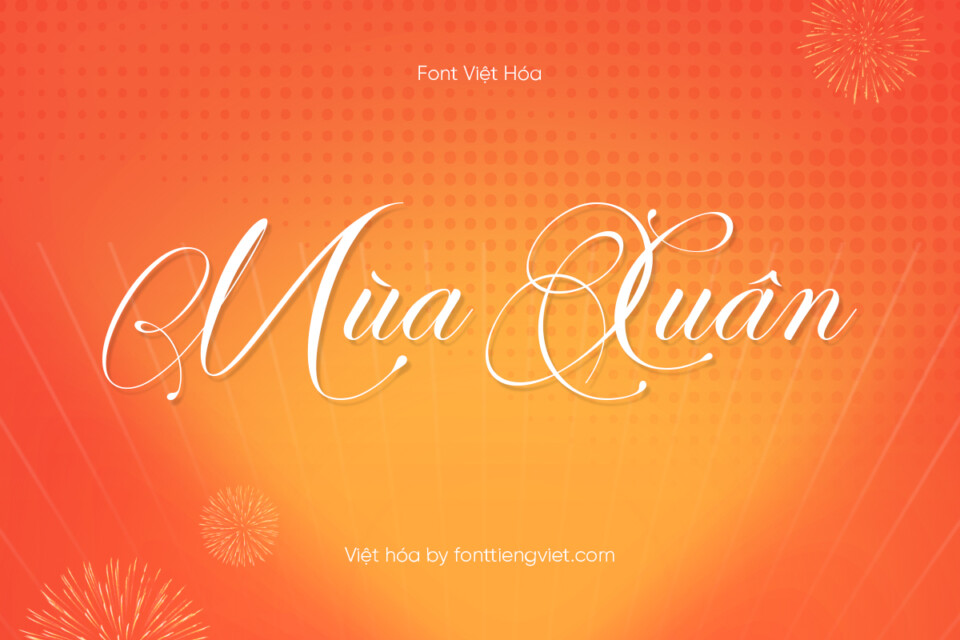
Tải Ngay Font Việt hóa 1FTV VIP Perfecto Calligraphy – Font tết Tuyệt Đẹp Cho Mùa Lễ Hội
Giới thiệu về bộ Font Việt hóa 1FTV VIP Perfecto Calligraphy – Font tết
Chào đón không khí rộn ràng của những ngày cuối năm, nhu cầu tìm kiếm các mẫu thiết kế mang đậm nét truyền thống ngày càng tăng cao. Trong đó, Font Việt hóa 1FTV VIP Perfecto Calligraphy – Font tết nổi lên như một lựa chọn hàng đầu cho các nhà sáng tạo. Đây là bộ Font Chữ nghệ thuật với những đường nét uyển chuyển, thanh thoát, mang lại sự sang trọng và ấm áp cho mọi bản thiết kế. Việc sử dụng font chữ này giúp các biểu ngữ, thiệp chúc mừng trở nên sinh động và chuyên nghiệp hơn bao giờ hết.
Đặc điểm nổi bật của Font Việt hóa 1FTV VIP Perfecto Calligraphy – Font tết
Bộ font này được tối ưu hóa hoàn toàn cho bảng mã tiếng Việt, giúp người dùng dễ dàng gõ các ký tự có dấu mà không lo bị lỗi hiển thị. Với phong cách Calligraphy hiện đại, các nét chữ được trau chuốt tỉ mỉ, tạo nên sự kết nối tự nhiên giữa các con chữ. Đây là công cụ đắc lực để thiết kế bao lì xì, thực đơn tiệc tất niên hay các hình ảnh quảng cáo cho dịp Tết Nguyên Đán.
Cách ứng dụng Font Việt hóa 1FTV VIP Perfecto Calligraphy – Font tết hiệu quả
Để phát huy tối đa vẻ đẹp của font chữ này, bạn nên kết hợp với các tông màu đỏ, vàng hoặc xanh lá đậm đặc trưng của ngày Tết. Độ tương phản cao và đường nét mảnh mai của font sẽ tạo nên điểm nhấn tinh tế trên nền thiệp chúc. Ngoài ra, việc sử dụng font làm tiêu đề cho các bài đăng mạng xã hội cũng giúp thu hút thị giác người xem một cách hiệu quả nhất.